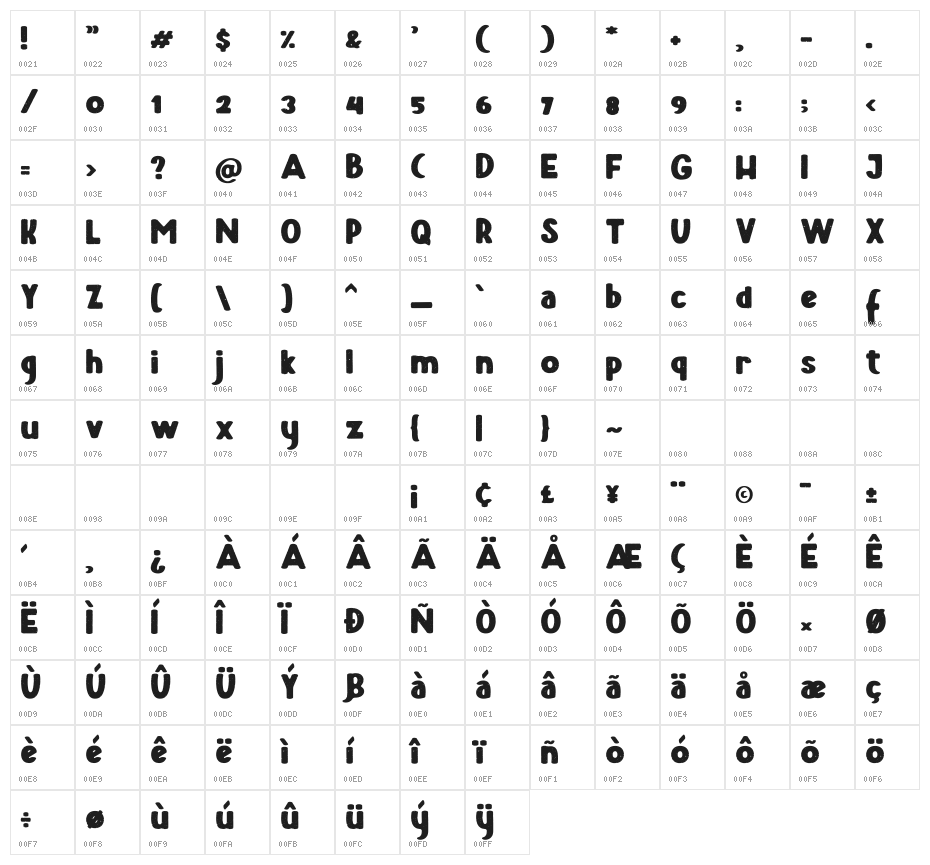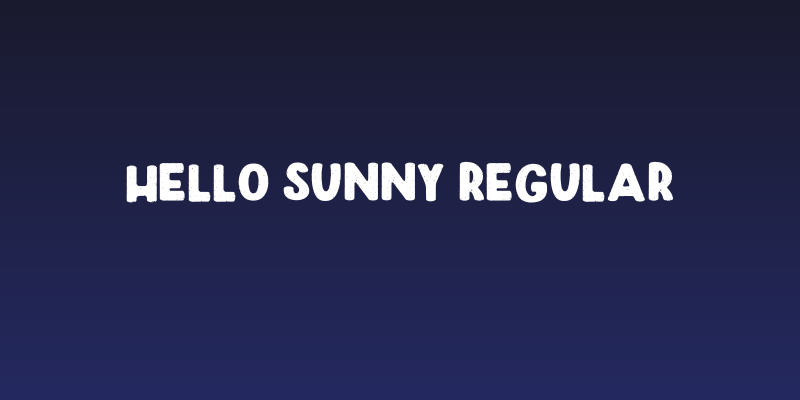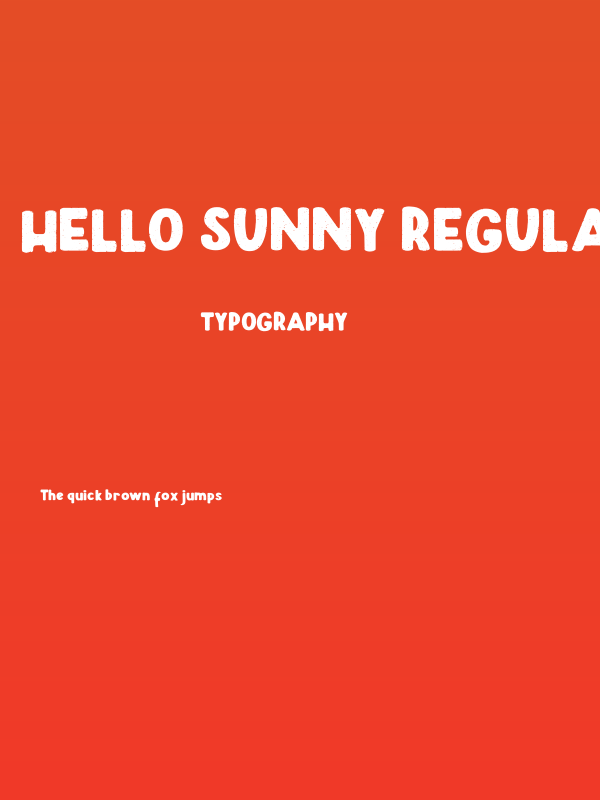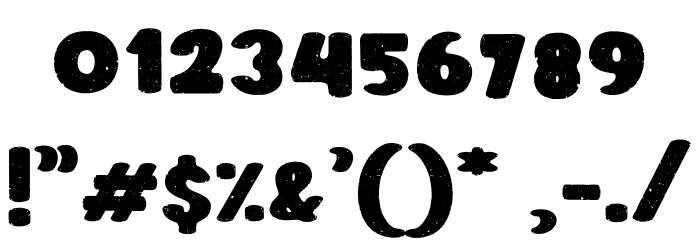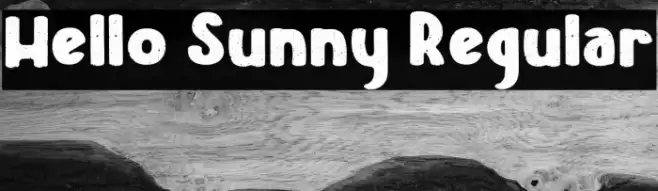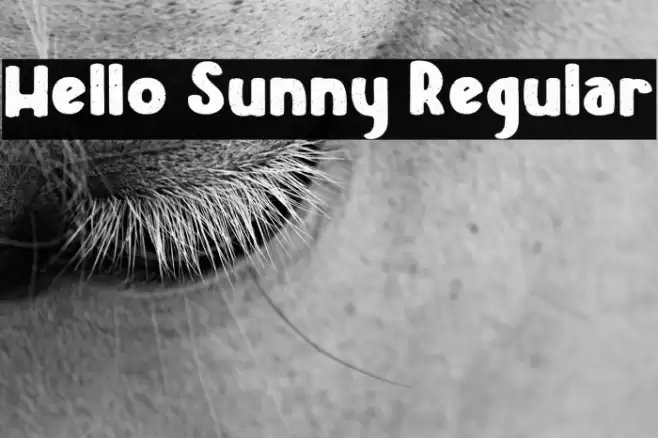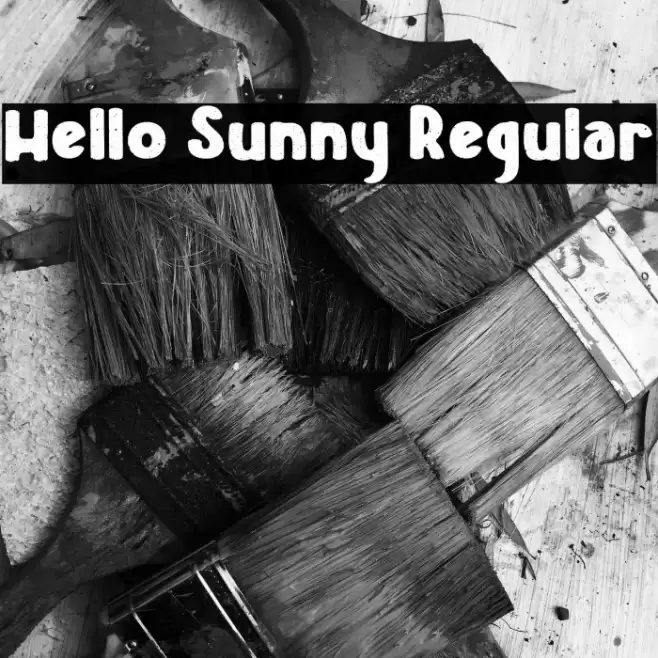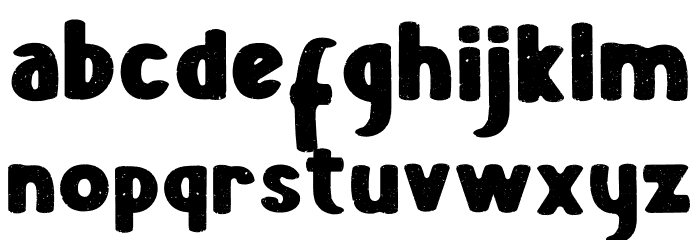
Hello Sunny Regular Font
✎ Comic
| عائلة الخط | Hello Sunny |
| الفئات | Comic |
| النمط العام | Vintage, Playful |
| مشاريع مقترحة | Ideal for branding, posters, children's books, and creative projects requiring a fun and engaging typeface. |